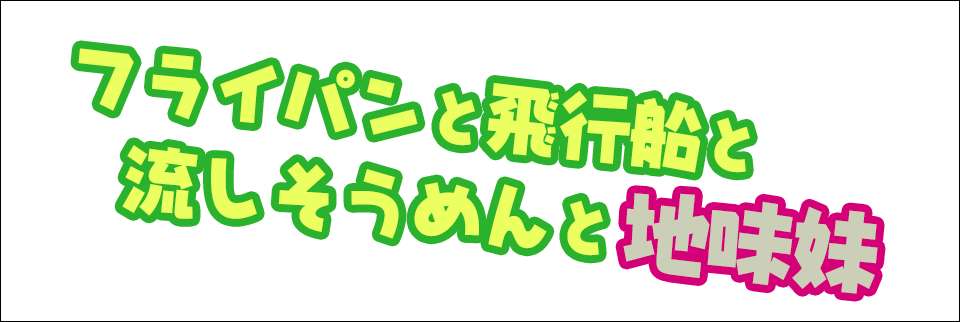
JTCじゃんけんU フォントの作例
JTCじゃんけんU フォントの作例です。
ポップ調のゴシック的なフォントです。柔らかく砕けた表現ができます。
JTCじゃんけんU フォントの作例:画像1
柔らかくポップな表現ができます。
JTCじゃんけんU フォントの作例:画像2
ライトノベルやコミックなどの文字としても利用しやすいフォントです。